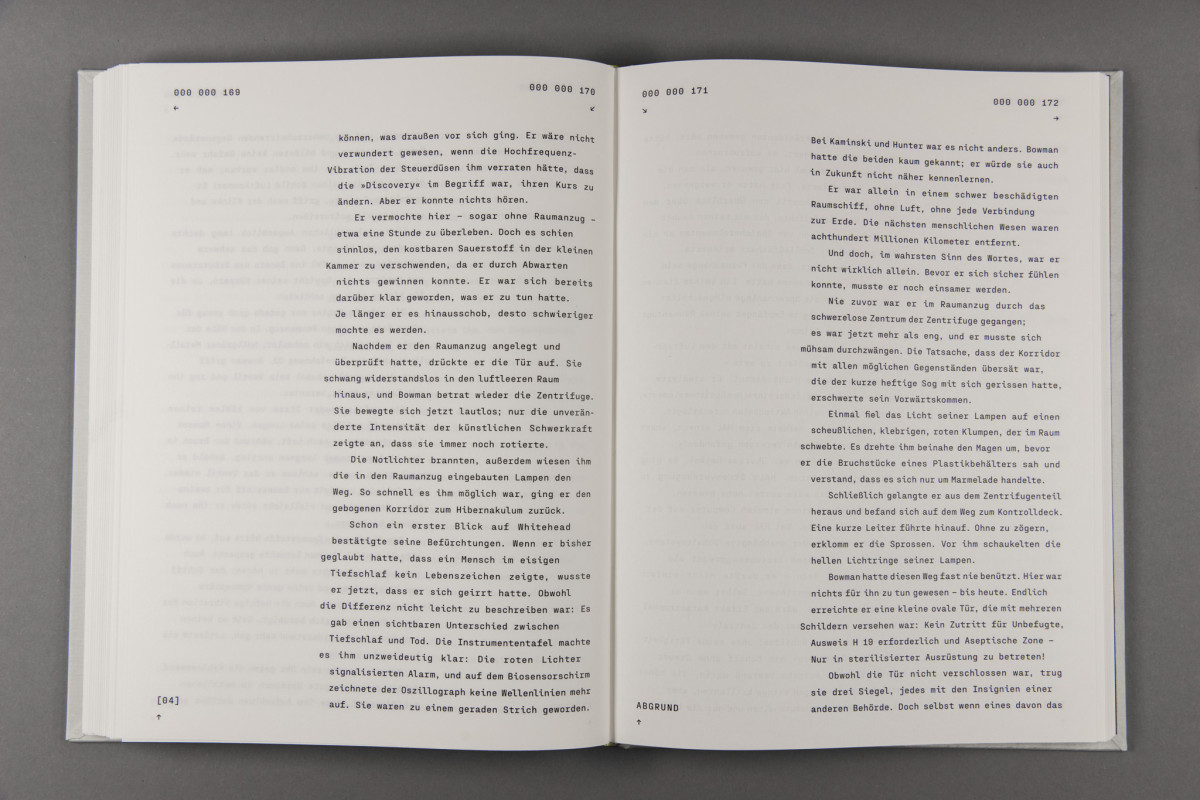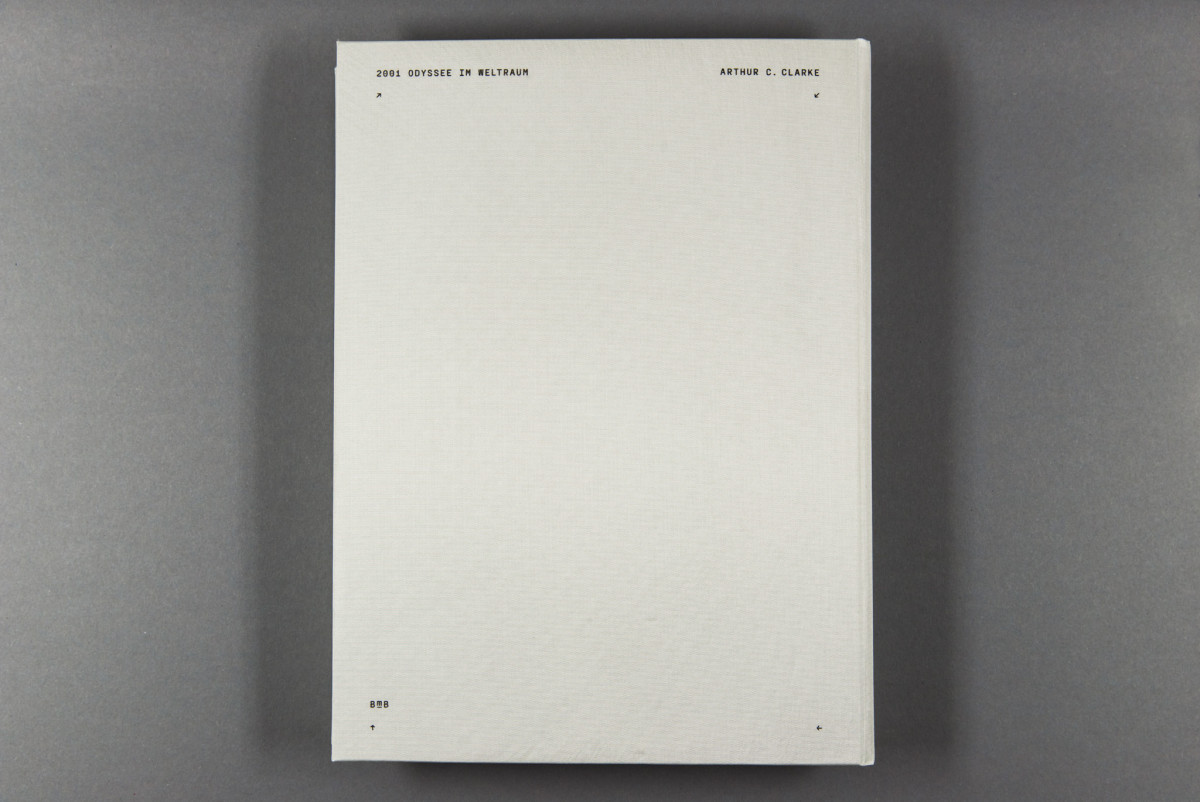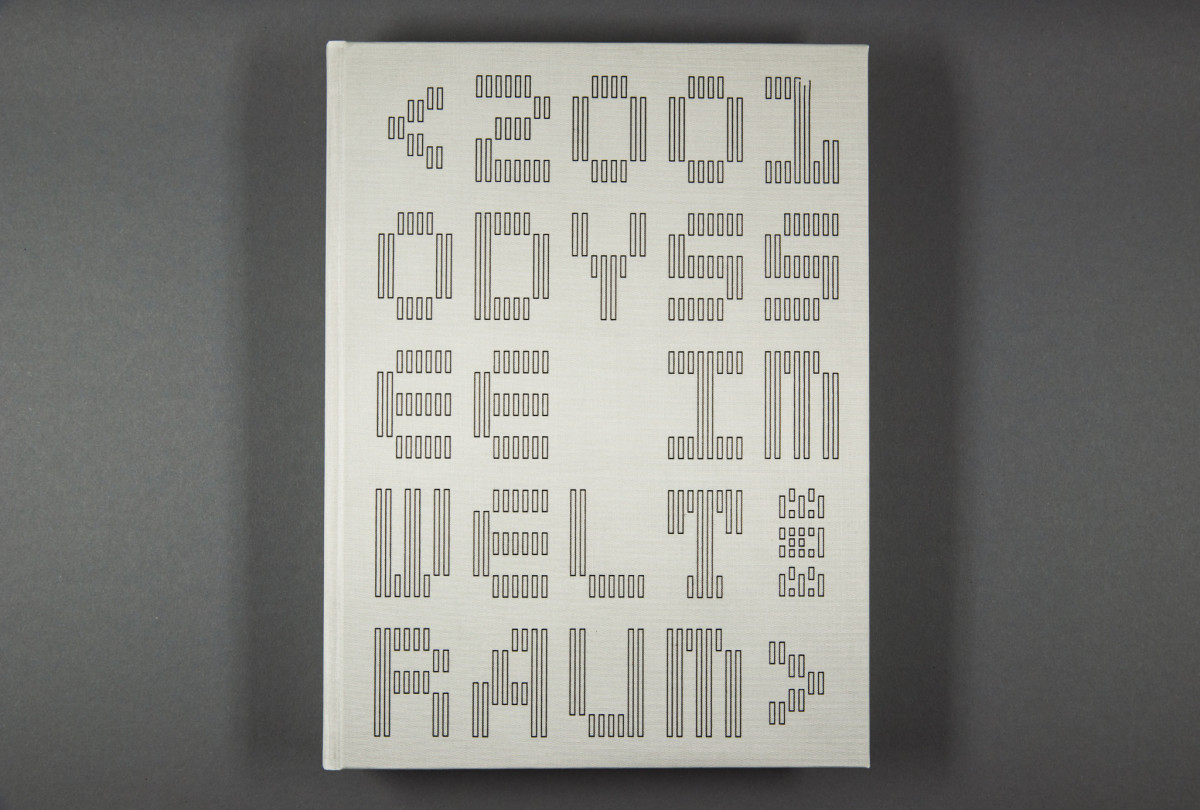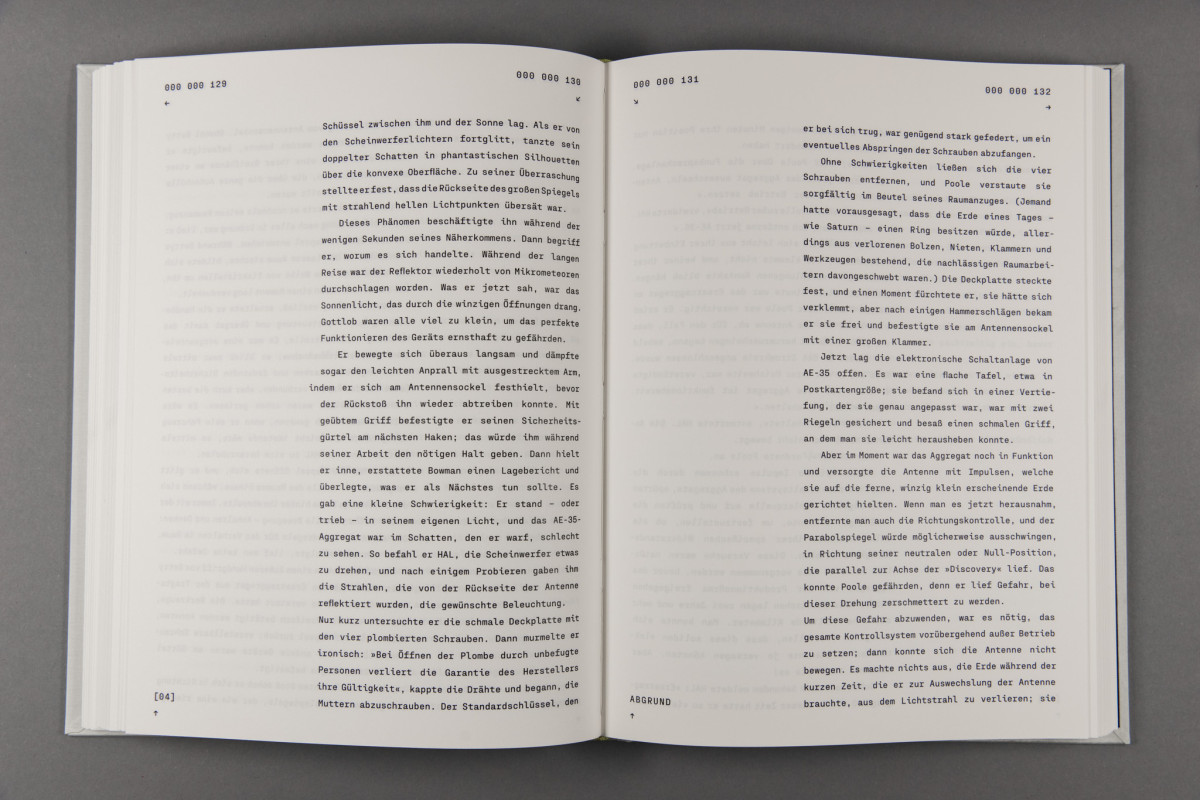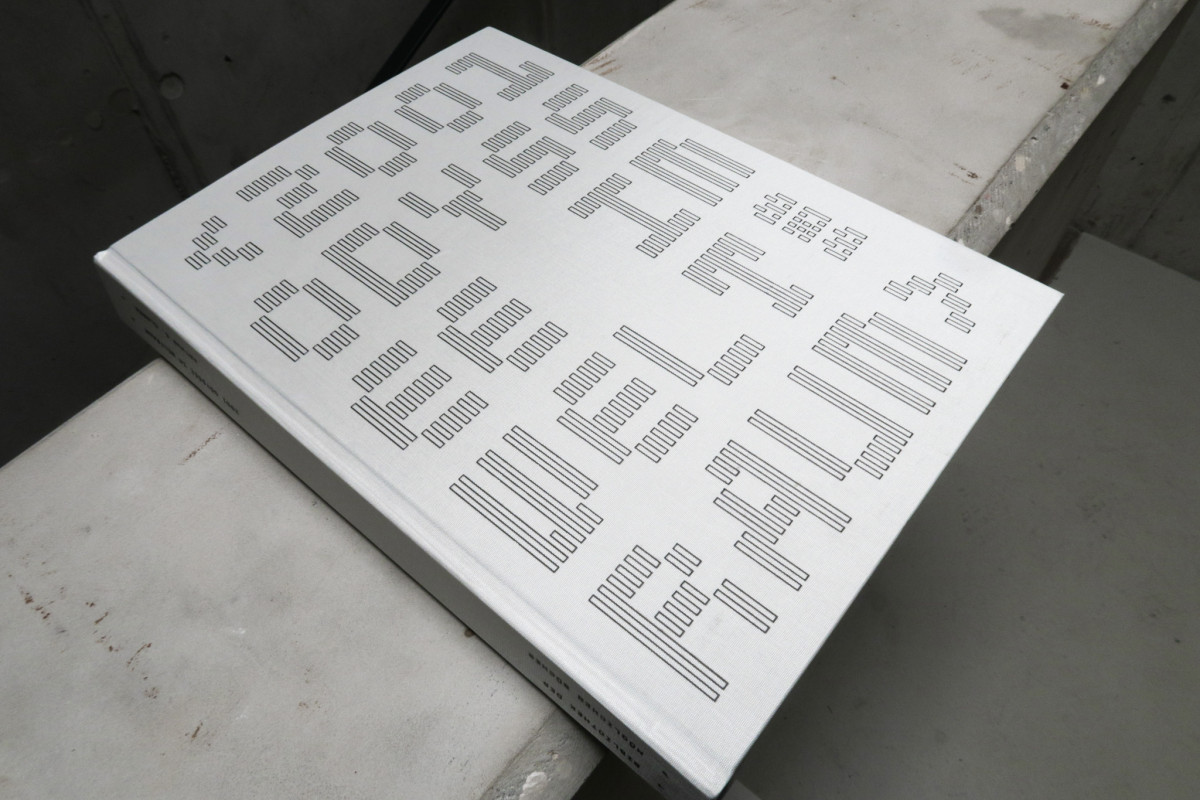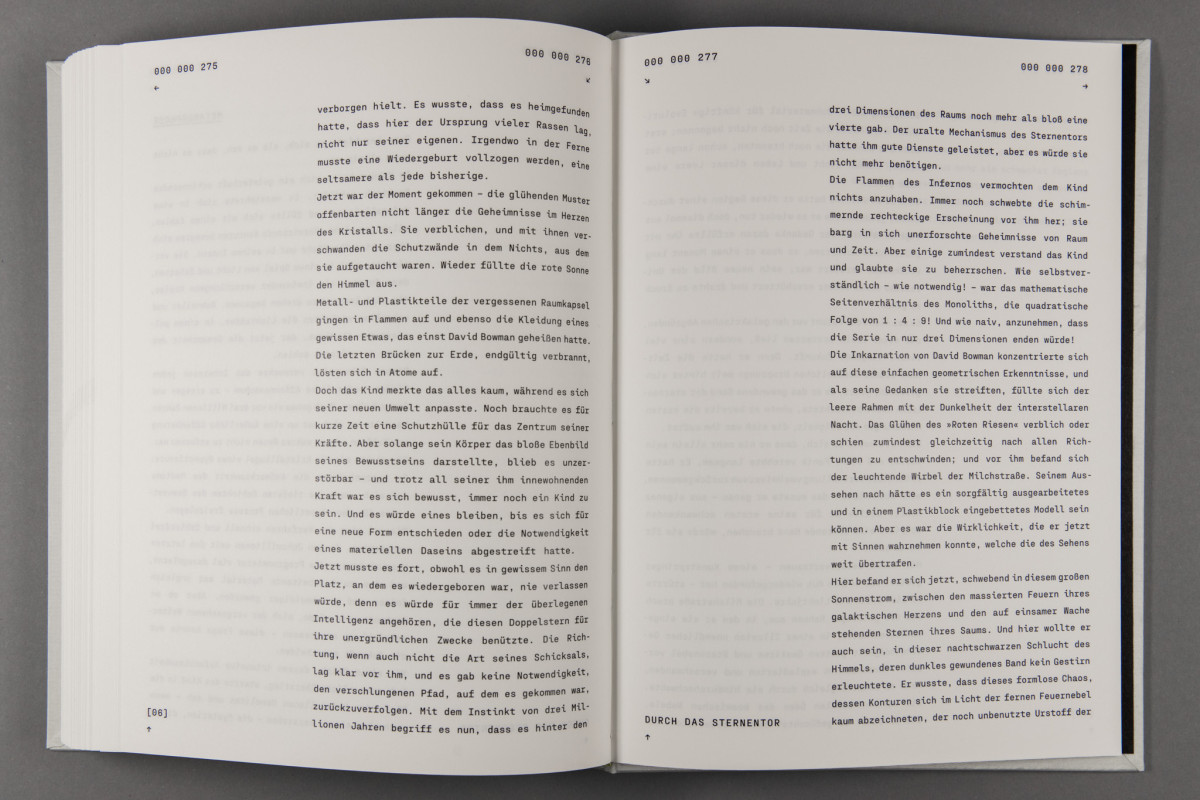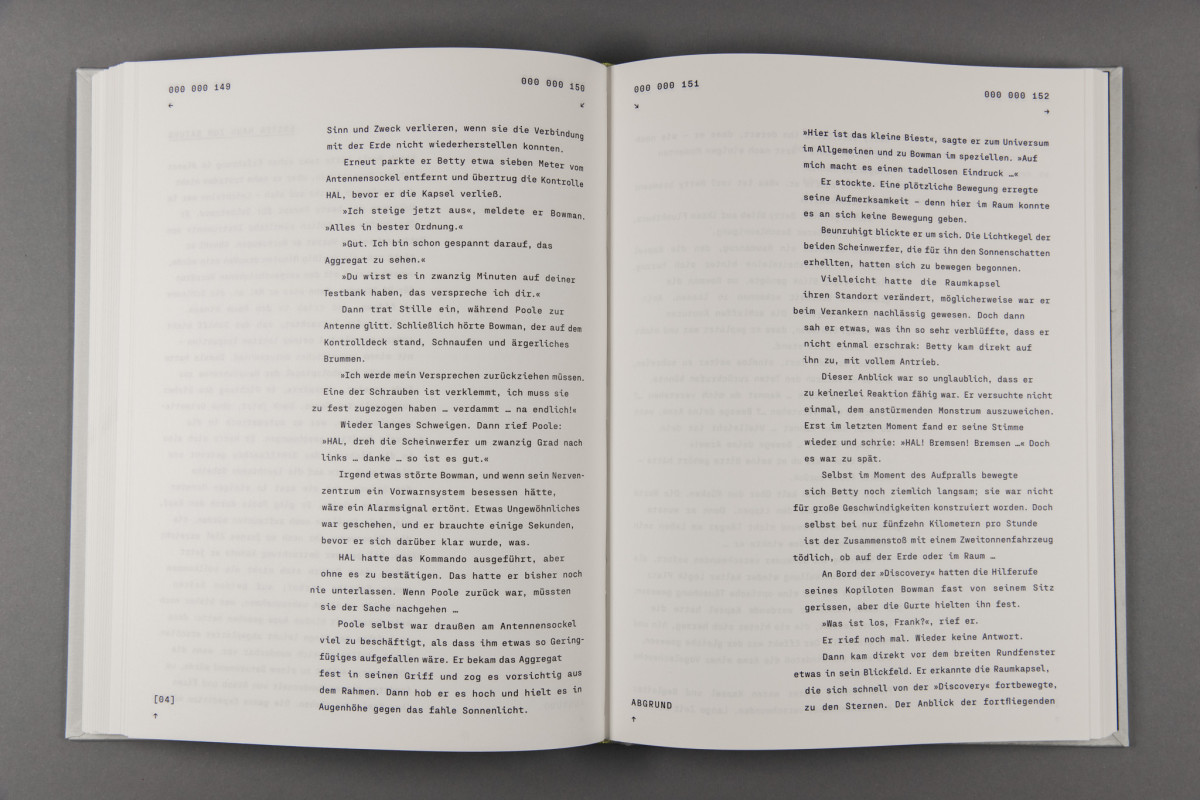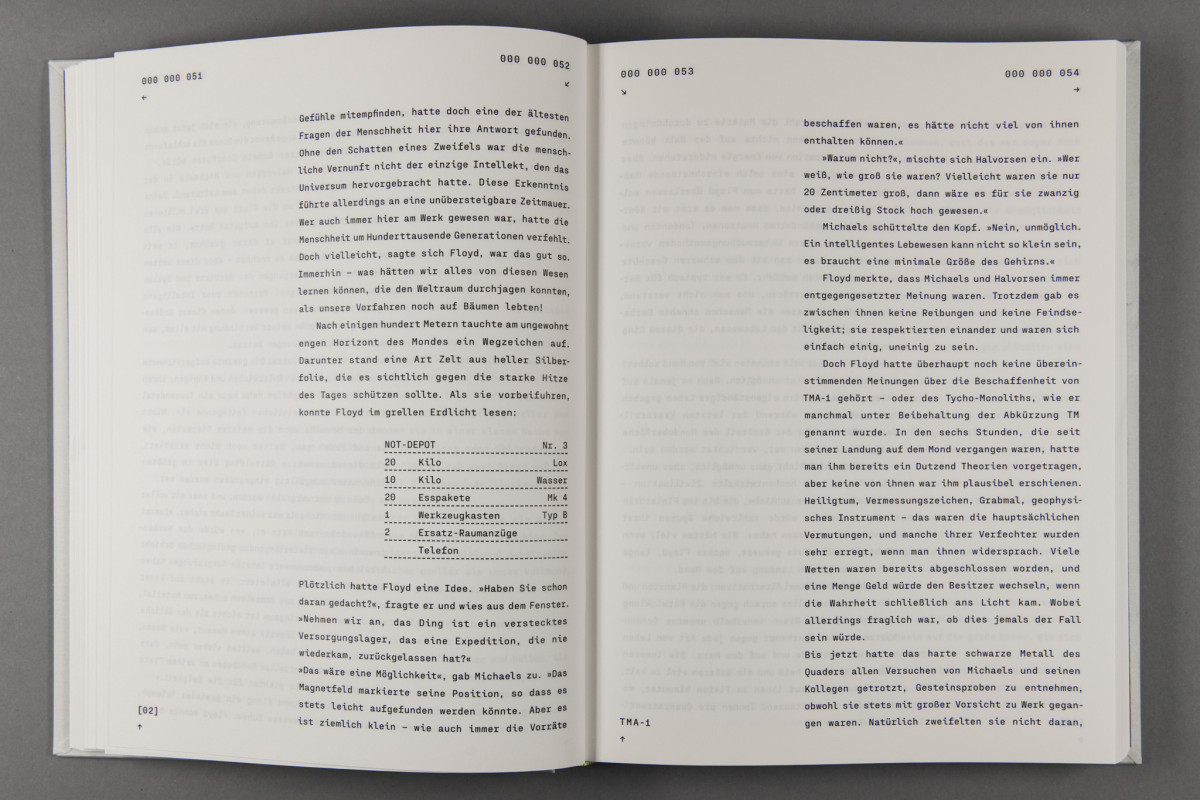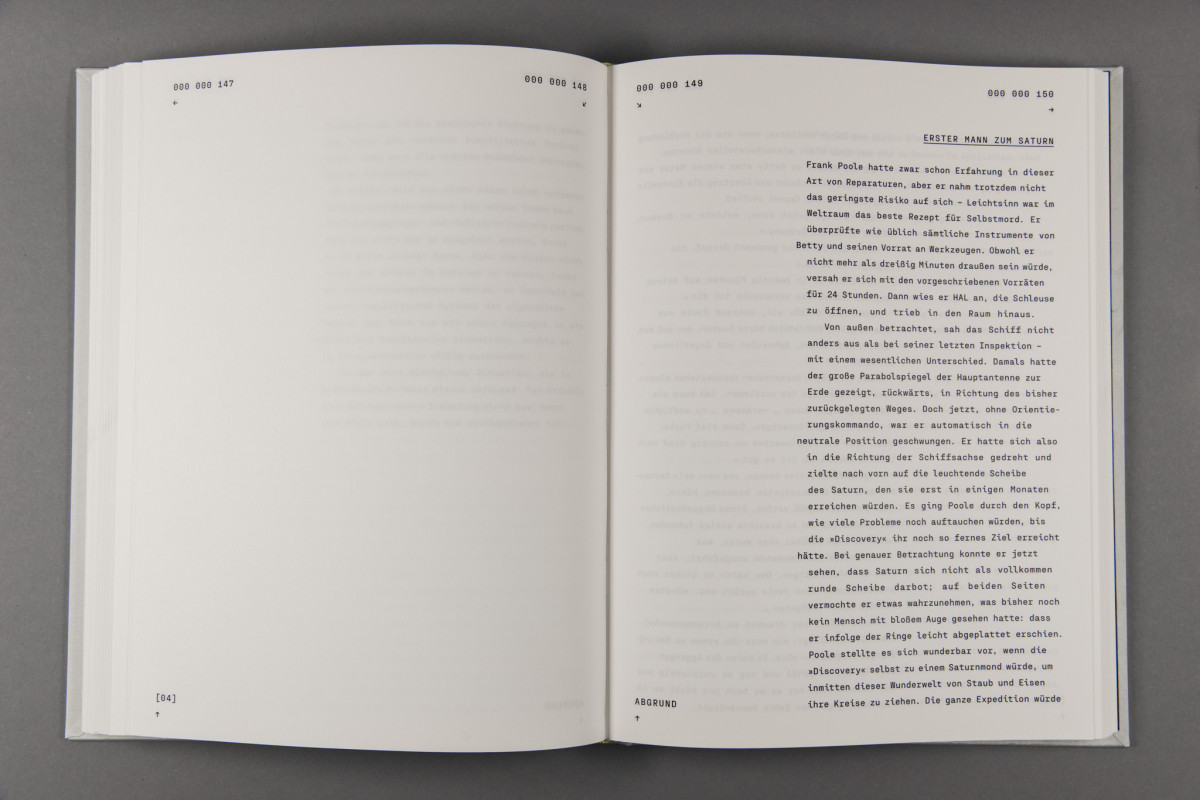
Im Rahmen des Buchgestaltungs-Kurses bei Prof. André Heers und Prof.in Annette le Fort zum Thema »DU UND ICH« gestaltete ich im Wintersemester 23/24 das Buch »Odyssee im Weltraum« von Arthuc C. Clarke – zum gleichnamigen Film von Stanley Kubrick – als Hardcover Bindung.
Die typografische Umsetzung besteht aus einem Blocksatz, der sich im Verlauf der sich immer weiter zuspitzenden Geschichte, mit der Malfunction des Boardcomputers HAL 9000, in einen Flattersatz übergeht. Verschiedene Hinweise des technischen Ausfalls werden durch nach links versetzte Ausbuchtungen einzelner Zeilen erfahrbar. Das Cover gleicht einer schriftgestalterischen Übersetzung von äußeren Raumschiff-Strukturen.
As part of the book design course taught by Prof. André Heers and Prof. Annette le Fort, the book 2001: A Space Odyssey by Arthur C. Clarke – based on the film of the same name by Stanley Kubrick – was designed as a hardcover edition during the winter semester 2023/24.
The typographic concept employs justified text, which gradually transitions into ragged-right setting as the narrative intensifies, culminating in the malfunction of the onboard computer HAL 9000. Indicators of the technical failure are conveyed through individually indented lines, offset to the left, creating visual disruptions in the text flow. The cover design constitutes a typographic interpretation of exterior spaceship structures.